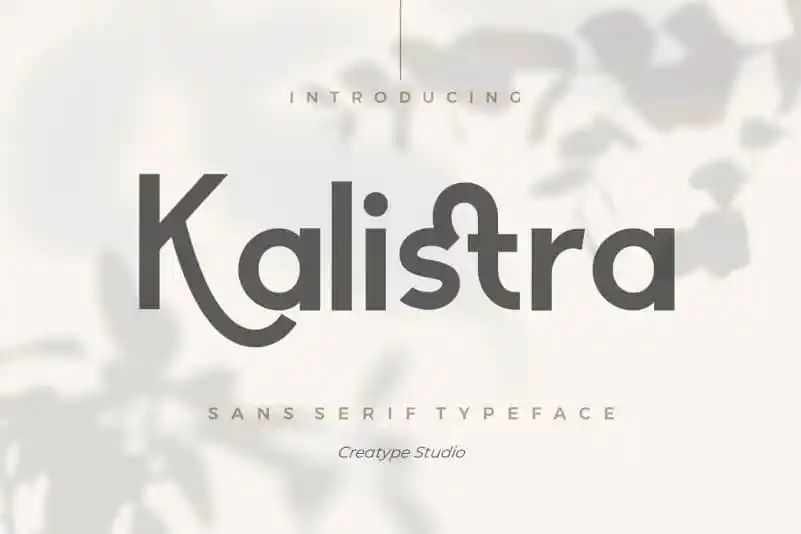
Kalistra Sans Serif Font – Download Grátis
Kalistra Sans Serif é uma fonte elegante e sofisticada inspirada em uma placa de restaurante dos anos 60, ideal para criar ambientes modernos e contemporâneos. Suas linhas leves e arredondadas dão um toque refinado a qualquer projeto, tornando-a perfeita para aplicativos variados como logotipos, banners, gráficos de marketing ou até mesmo fontes de texto em sites profissionais. Numa era onde o design minimalista é comum, Kalistra se destaca pela sua elegância e simplicidade. Perfeito tanto para ambientes urbanos quanto rurais, essa fonte cativa a atenção por meio de seu estilo único que evoca uma vibe nostálgica dos anos 60, mas mantendo-se atual e inovador, fazendo do Kalistra Sans Serif um recurso gráfico imprescindível para qualquer designer gráfico em busca de um visual moderno e sofisticado.